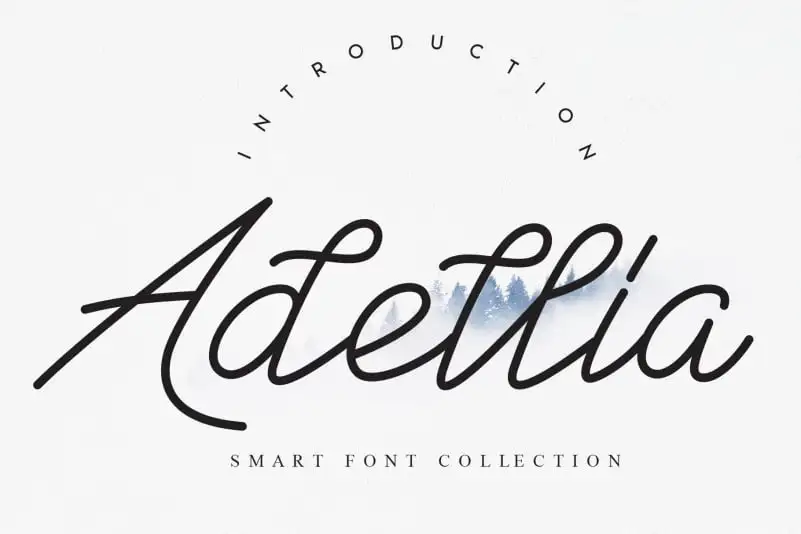
Adellia Handwritten Font – Download Grátis
A fonte Adellia Handwritten é uma criação do designer creativeletter que oferece aos usuários uma experiência única e especial. Com linhas fluidas e sentimentos amigáveis, essa fonte permite que as pessoas expressem sua criatividade de maneira ímpar. Seja para personalizar mensagens em cartões de aniversário ou criar um design atraente para seu website, Adellia Handwritten tem o poder de torná-lo único e envolvente. Seu charme delicado e seu estilo elegante tornam-se perfeitos para textos pessoais e experiências memoráveis. A fonte adora ser usada em nomes de empresas, design gráfico ou até mesmo em letras livres e desenho artístico, proporcionando uma sensação fresca e encantadora ao trabalho final. Adellia Handwritten oferece aos artistas, designers e escritores a oportunidade de trazer vida às palavras, tornando-a uma escolha definitiva para quem busca algo que seja único, convidativo e emocionante.